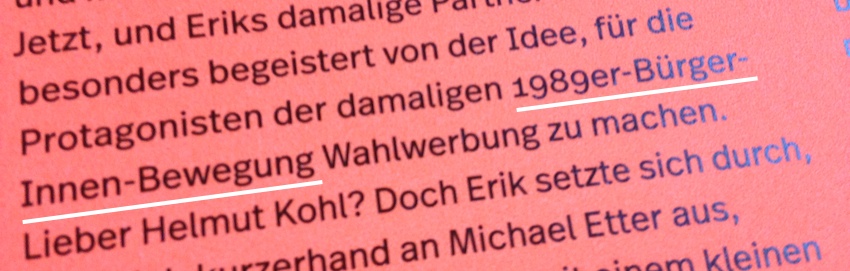
Großküchensenfeimer
unausprechbarkeitlichkeitstagesweltrekord. ; )
Ich mag eh keinen Senf, deswegen bevorzuge ich eindeutig den Großküchenketchupeimer ſtatt des Großküchenſenfeimers, für deſſen korrekte Decodierung ich viel zu lange gebraucht habe ... ;-)
... oder den Großküchentzatzikiſauceneimer zum Buchſtabenſalat ... ;-)
… ſtatt des Großküchenſenfeimers, für deſſen korrekte Decodierung ich viel zu lange gebraucht habe ...
Ich muß ehrlich sagen, ich habe daran herumbuchstabiert, obwohl im Text zuvor ein Großküchenmayonnaiseneimer vorgekommen war. :-(
Ich habe gerade das Wort Versalziffern versucht zu whatsappen und das iPhone hat Versalzungen daraus gemacht und ich habe ganz schön lange gebraucht herauszufinden was Versal-Zungen sein sollen ...  :oops:
Vielleicht das Gegenteil von RoMi oder frenetik, die hier nur klein schreiben – jemand, der nur in Großbuchstaben redet (s. gespaltene Zunge, fremde Zunge)  :hammer:
so etwas wie Serifen?
Genauer gesagt: Üerlange Serifen, die aus Versalien rausragen ...
Heidenei, bis ich auf die wahre Bedeutung der VersalZungen gekommen bin ... ;-)
Genauer gesagt: Üerlange Serifen, die aus Versalien rausragen ...
Ich dachte als erstes an die zungenartigen Querstriche, die es eigentlich nur bei Versalien gibt:
Hier frage ich mich jetzt, ob das entsprechende Gegenstück eine 1989er-Bürger-Bewegung oder eine 1989er-Bürger-Außen-Bewegung sein soll …
Aus der Spiekermannbiografie, S. 135.
Das passt schon irgendwie. Bei den meisten von uns Ossis fand der Protest gegen das Regime überwiegend im Inneren statt – der Familie, des eigenen Kopfes …
Ein Klassiker! Händchenhalten für Fortgeschrittene.
Oder für Körperbehinderte. Ich hatte mal in einer Gruppe, die sich regelmäßig traf einen beidseitig Armamputierten, der recht geschickt, auch schreiben, uns umblättern von Buchseiten mit dem Fuß bewerkstelligte. Da ich wusste, das dieser Mensch kommt, hatte ich mr zu diesem Termin den rechten Fuß /den anderen natürlich gleich mit) einer gründlichen Schrupp- und Hornhaut-Entfernungsbehandlung unterzogen. Bei treffen schüpfte ich dann rasch aus dem Schuh, und streckte meinen Fuß dem verdutzen Armlosen zur Begrüßung entgegen, was der natürlich auch begriff, und dann haben wir eben ein "Schake-Feets" gemacht. Das ging auch erstaunlich gut, wenn auch recht ungewohnt und eher unüblich ist. Allerdings gab es schon bei uns beiden was zu lachen. Ach so, er hatte auch eine wirklich schön leserliche Fußschrift. Das bekomme ich aber nicht hin...
Noch heute bin ich daheim fast immer nur barfuß, und wenn mir z.B. ein Stift heruterfällt, dann bücke ich mich nicht, sondern hebe es mit den Zehen auf, wofür hat man die sonst auch?
So viel zum beinhalten...
… und wenn mir z.B. ein Stift heruterfällt, dann bücke ich mich nicht, sondern hebe es mit den Zehen auf, wofür hat man die sonst auch?
[klugscheiszmodus]Du kriegst mit den Zehen ein ganzes Stift gehoben? Etwa das St.-Marien-Stift Wolgast? Was für eine Schuhgröße hast Du?[/klugscheiszmodus]
der recht geschickt, auch schreiben, uns umblättern von Buchseiten mit dem Fuß bewerkstelligte.
Habe etliche Contergangeschädigte im Bekanntenkreis und deren Fußfertigkeiten, von Geburt an geübt, sind tw, auch ziemlich beeindruckend. Hat allerdings auch den Haken, dass die unnatürliche Belastungen zum vorzeitigen Verschleiß führen mit entsprechenden Schmerzen etc.
Ist ja auch bequemer.
Hachja, vor allem wenn der Bauch eines Tages so im Weg ist ...
[klugscheiszmodus]Du kriegst mit den Zehen ein ganzes Stift gehoben?
Eigentlich ist gegen "es" doch nix einzuwenden angesichts des "z.B.", was ja viel derdiedas ersetzt ;)
"ihn" wär ja auch nicht richtig, Lehrlinge darf man nicht mit den Füßen berühren.